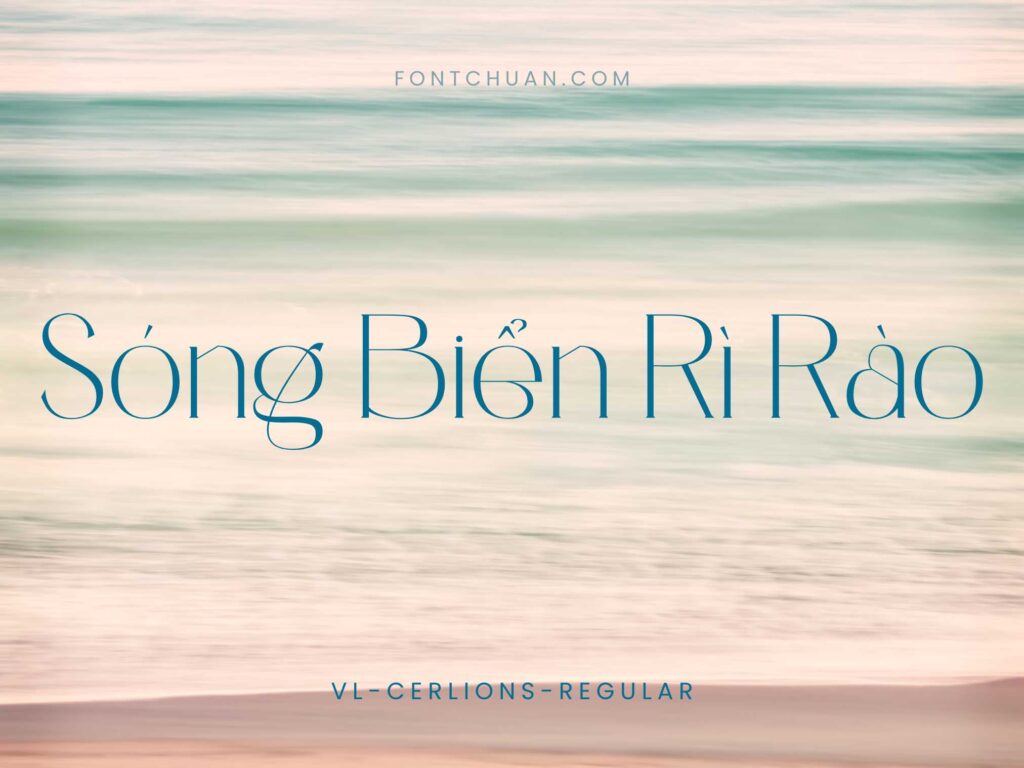
Font VL Cerlions Việt Hóa
Tác giả Font: Brandsemut
Việt hóa bởi: Font Việt Linh
VL-Cerlions-Regular là một phông chữ serif mang phong cách hiện đại và tinh tế, được thiết kế bởi BrandSemut. Phông chữ này có các đường nét thanh mảnh và uyển chuyển, tạo nên sự thanh lịch và chuyên nghiệp cho các thiết kế. VL-Cerlions-Regular đã được Việt hóa bởi Việt Linh, hỗ trợ đầy đủ các ký tự tiếng Việt, giúp người dùng dễ dàng sử dụng trong các dự án sáng tạo. Phông chữ này được thành viên Font Chuẩn sưu tầm và đăng tải nhằm phục vụ nhu cầu thiết kế đa dạng.
Với thiết kế thanh lịch và rõ ràng, VL-Cerlions-Regular phù hợp cho các ứng dụng như tiêu đề, văn bản dài, thiết kế logo và các ấn phẩm in ấn. Trong lĩnh vực sự kiện, phông chữ này có thể được sử dụng trong các dịp như lễ cưới, hội nghị và các sự kiện văn hóa. Ngoài ra, VL-Cerlions-Regular cũng thích hợp cho các ngành nghề như quảng cáo, giáo dục và công nghệ.